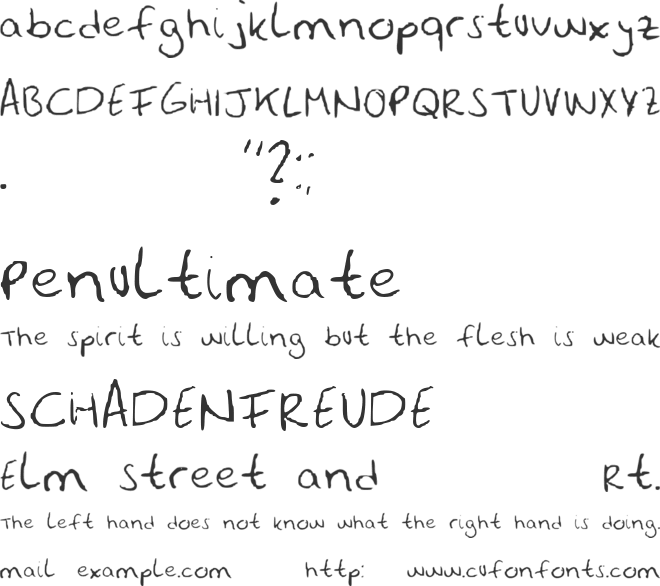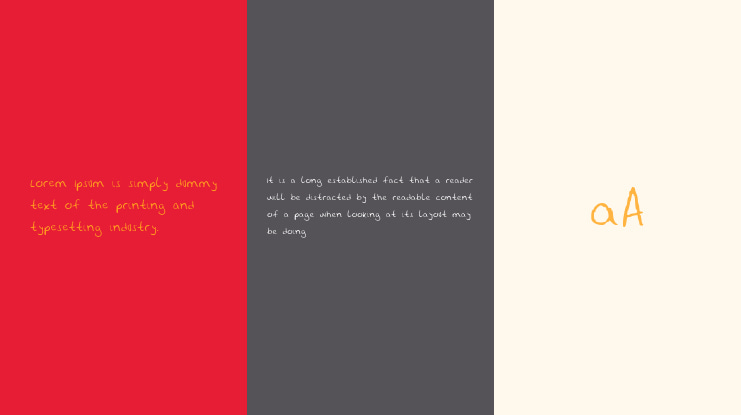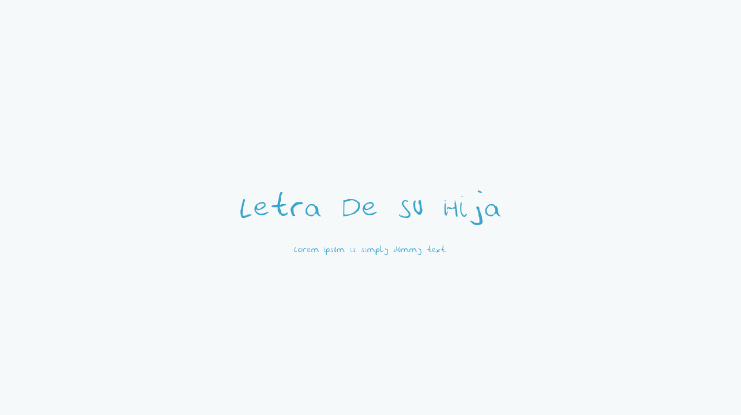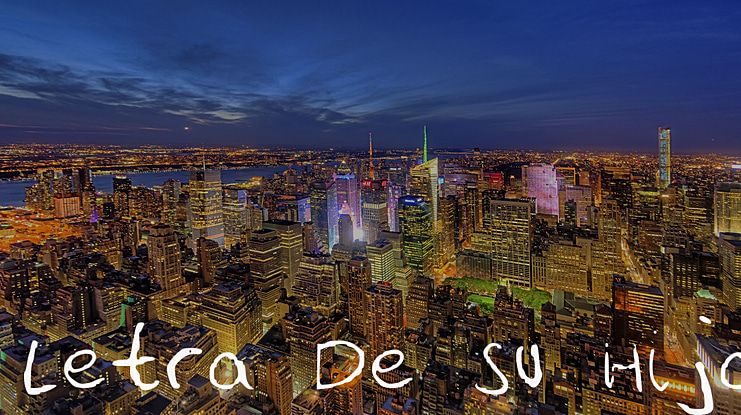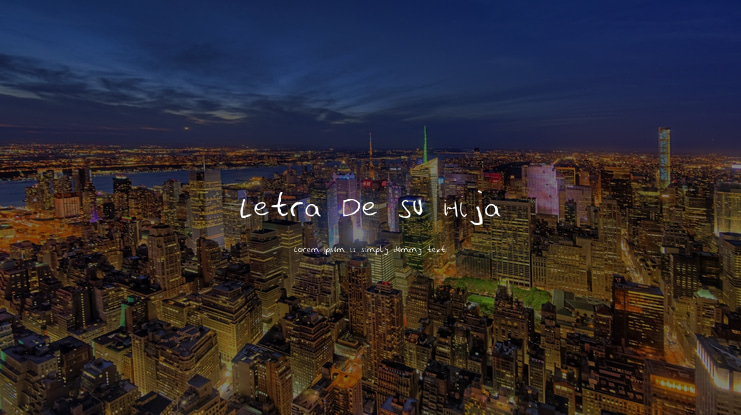
Letra De Su Hija Font
Tipografia "letra de su hija", parte del proyecto transmedia "Los días sin ti". Trabajo Fin de Máster de Comunicación Móvil y Contenido Digital de la Universidad de Murcia.
Autora: María del Carmen Martínez García
Año: 2022